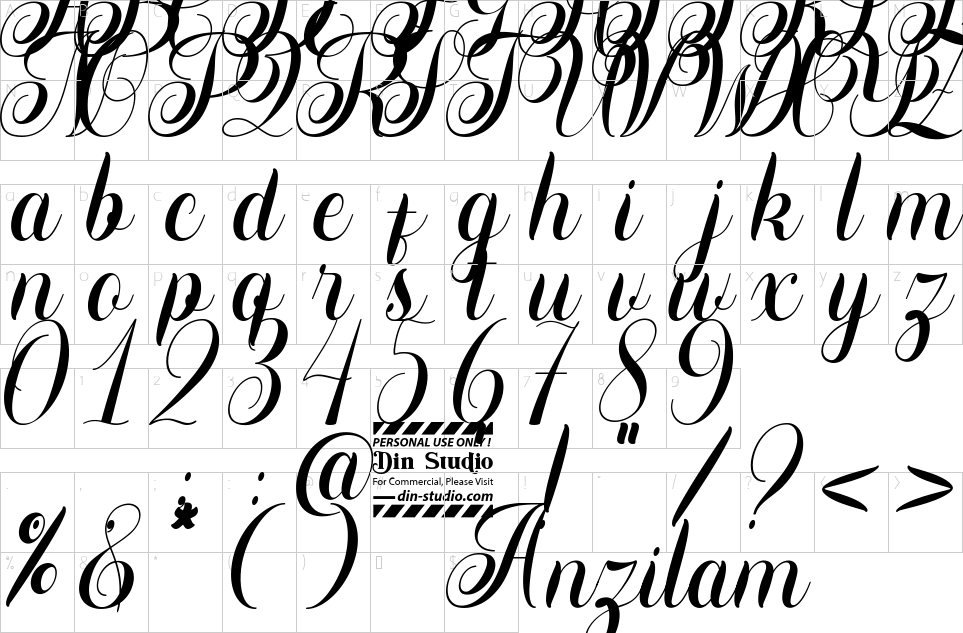
Anzilam é uma fonte de graça que oferece um visual elegante e sofisticado, adequado para qualquer tipo de projeto de design, seja ele para um site profissional, um livro de arte ou até mesmo um simples e-mail personalizado. Desenvolvida pelo designer desconhecido, essa fonte foi projetada com cuidado para oferecer um grau de controle incrível, permitindo que você personalize a aparência de seu texto para atender às suas necessidades específicas. Para os usuários de sistemas Windows e Mac, Anzilam font está disponível gratuitamente. A fonte foi baixada 309 vezes, demonstrando seu valor e a qualidade do seu design. Anzilam é uma excelente escolha para quem busca um recurso gráfico de qualidade sem precisar gastar dinheiro. Com seu design cuidadosamente planejado, você pode dar um toque único ao seu projeto, seja ele para um trabalho profissional ou um projeto pessoal.